Rubrikator
»Rubrikator« ist eine Berufsbezeichnung für einen Gehilfen eines Schreibers (siehe Kalligrafie) oder Kopisten eines mittelalterlichen Skriptoriums (lat. scriptorium für Schreibstube), der nach dem Schreiben eines Textes – ab Mitte des 15. Jahrhunderts nach dem Druck einer Inkunabeln – die Überschriften (Headlines), Initialen, Lombarden, Buchstabenverzierungen oder Zeilenfüller in Büchern (z.B. Kodizes) oder Manuskripten (z.B. Urkunden) in einer Farbauszeichnung, in der Regel mit rötlicher Tinte, händisch auszeichnete. Substantiv »Rubrizierung«; Verb »rubrizieren«.
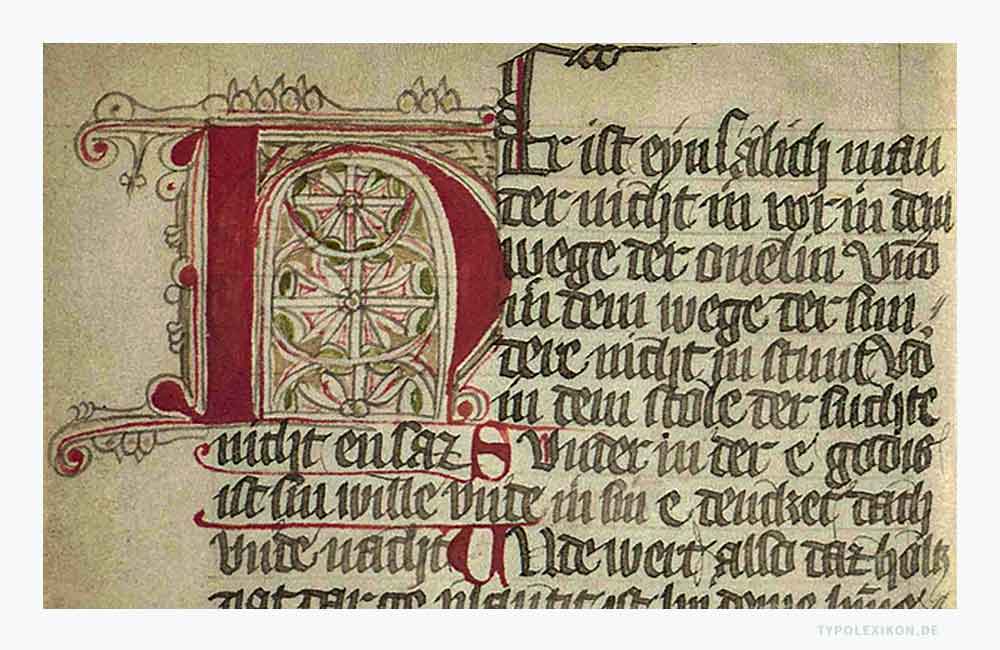
Sinngemäß bedeutet Rubrikator »Rotmacher«. Etymologisch rührt diese Bezeichnung von lat. »rubrum« für »rot« zu lat. »rubrica« für »Rötel zu lat. »rubricare« zu mhd. »rubrike« für »rote Tinte« bzw. »rot anmalen«.
Die Rubrizierung war die früheste Methode einer systematischen Schriftauszeichnung, Gliederung und Strukturierung. In der Paläografie werden diese in Teilen zum Buchschmuck gezählt. Sowohl die Bezeichnung »Rubrik« als auch der typografische Terminus »Auszeichnung« rührt daher.
Für die Rubrizierung wurden in der Regel Schreibflüssigkeiten wie Tinten, Tuschen und Temperafarben, die bis zur industriellen Chemie manuell aus Pflanzen (z.B. Moosflechten für Grün, Gummiarabikum als Bindemittel, Nelkenöl zur Konservierung, gallierte Eichenblätter als Gerbsäure), Steinen (z.B. Lapislazuli für Blau) und Tieren (z.B. Purpurschnecke für Purpurrot, Tintenfisch für Sepia) hergestellt wurden. Zinnoberrot (Cinnabarit) galt als die günstigste Auszeichnungsfarbe, blaue und grüne Pigmenten waren hingegen sehr kostbar, Purpur nahezu unbezahlbar, weshalb Purpur auch den höchsten Würdenträgern (Könige, Fürsten, Kardinäle) vorbehalten war.
Da Skriptorien über Jahrhunderte mehrheitlich eine Dienstleistung katholischer Klöster (z.B. des Ordens des Heiligen Benedikts) war, wurden Tätigkeiten dieser Art an mehr oder weniger begabte Ordensbrüder (Mönche, Pater oder Frater) delegiert, die für diese Art von Auszeichnungen und Rubrizierungen zuständig waren.
Ab dem 14. Jh. mit Zunahme der juristischen Kanzleien sowie ab Mitte des 15. Jh. durch die neu entstandenen Offizinen, wurde diese Tätigkeit auch außerhalb von Klöstern, insbesondere in Offizinen der Prototypografen ausgeübt. Oft geschah dies in Personalunion eines Wiegendruckers oder Illuminators.
Buchstaben oder Worte, die von einem Rubrikator ausgezeichnet oder korrigiert werden sollten, wurden von den Schreibern, Kopisten oder Frühdruckern mit Platzhaltern, sogenannten »Repräsentanten« versehen.
Von Hand eingefügte Rubrizierungen gehören in Frühdrucken (Wiegendrucken) noch zum Standard, welcher aber ab Anfang des 16. Jh. aufgrund monetärer und geänderter Lesegewohnheiten sukzessive verschwand. Während dieses Paradigmenwechsels arbeiteten Typografen, Kalligrafen, Rubrikatoren und Illuminatoren gemeinsam an der Herstellung von Druckerzeugnissen.